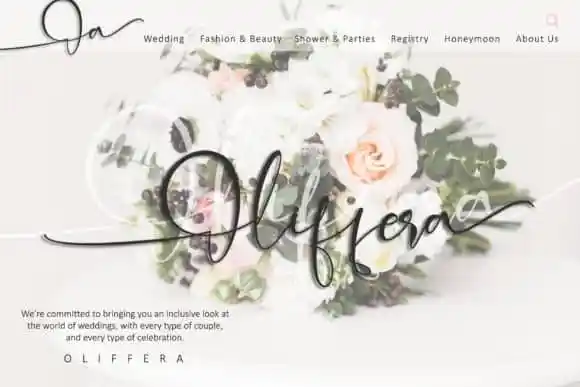
Alleffra Calligraphy Font – Download Grátis
Introduzimos a Alleffra Calligraphy Font. Esta é uma tipografia script moderna que transmite beleza e originalidade. Se apaixonar pela sua sensação autêntica, é perfeita para criar cartões de aniversário arrasadores, arte de papelaria bela, posts de mídia social atrativos e muito mais. Perfecta para decorar sus eventos especiais, seja um casamento ou uma celebração particular. Transforme seus materiais em verdadeiros trabalhos de arte com esta fonte exclusiva. Descubra por que a Alleffra Calligraphy Font é tão especial.